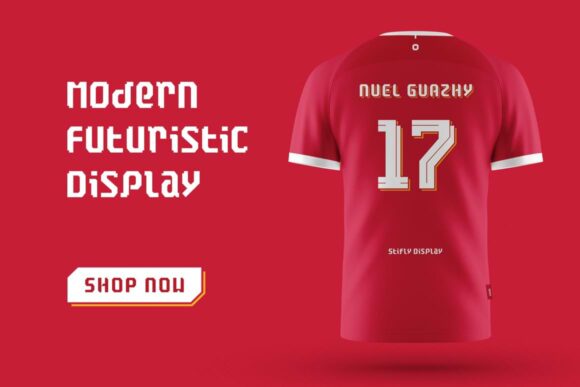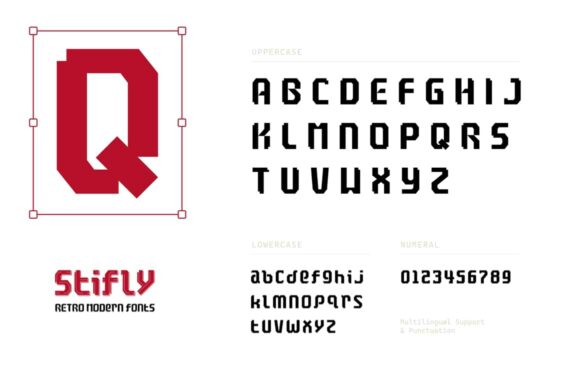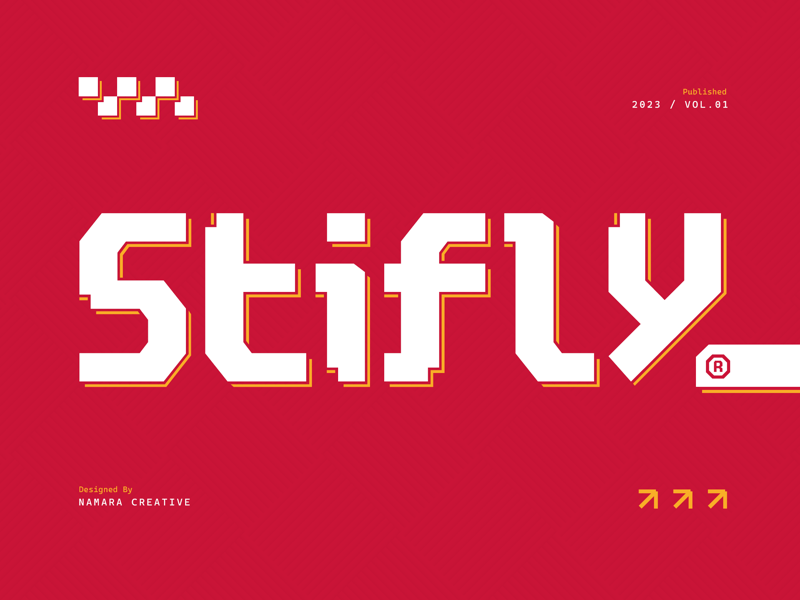
Stifly: Free Pixelated Sans-Serif Font
Stifly ist eine kostenlose Schriftart, erstellt von Namara Creative. Es handelt sich um eine serifenlose Schriftart mit einem pixelierten Design, das ihr einen modernen und futuristischen Look verleiht. Diese Eigenschaft macht sie perfekt für verschiedene grafische Projekte, einschließlich ihrer Verwendung auf Sporttrikots, wie im untenstehenden Bild gezeigt.